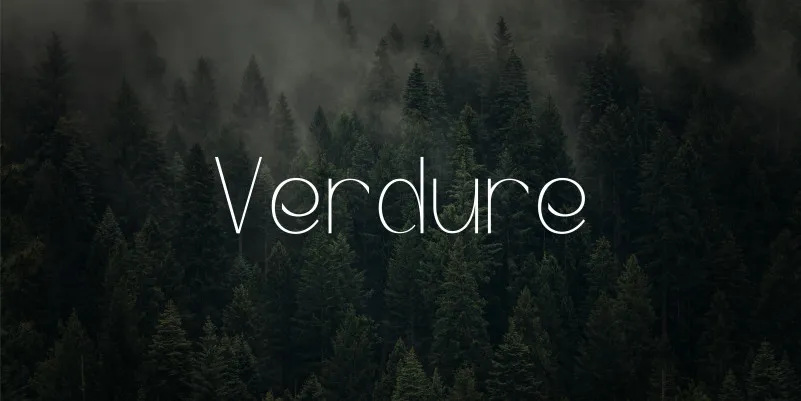
A Verdure Font é uma exuberante seleção do design do designer discant, inspirada na natureza brasileira. Seus traços elegantes retratam os frondosos pinheiros e as árvores altas que se curvam sob o sol, além das folhas verdes onduladas de densos matagios, tudo em uma tipografia com design para uso em exibição ou display. Este font é perfeito para marcas orgânicos e luxuosos, oferecendo um aspecto natural e harmonioso. Suas linhas possuem uma clara contraste que culmina em uma estética elegante e atraente. O modo de fluxo do font, suave e sofisticado, retorna usuários diretamente ao conforto dos ambientes naturais. A Verdure é uma opção perfeita para quem busca um touch natural na comunicação visual com design para uso exibicional.